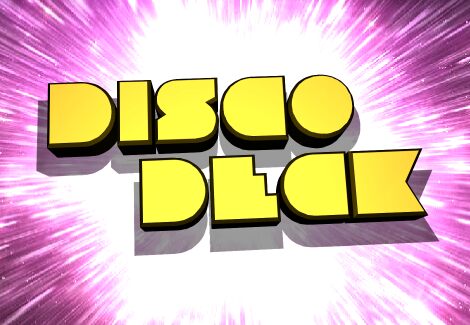
Disco Deck Italic od Iconian Fonts to groovy krój typu display, który przenosi Cię prosto na oświetlony neonami parkiet. Grube, pochylone litery sprawiają wrażenie, jakby ślizgały się po linii podstawowej, a wyraziste, zaokrąglone kształty przywodzą na myśl płyty winylowe i kule dyskotekowe. Zwarty rytm i pochylenie nadają każdemu słowu dynamiki, jakby tekst był uwięziony w błyskach stroboskopu.
Dzięki Disco Deck Italic nagłówki od razu krzyczą „impreza”, zanim jeszcze przeczytasz słowo. Ten darmowy font to naturalny wybór na klubowe ulotki, plakaty muzyczne, oprawę festiwali, grafikę w stylu retro, logotypy wydarzeń czy wyraziste gadżety. Świetnie sprawdza się w dużych rozmiarach – niech gra główną rolę, a w mniejszych tekstach połącz go z prostym, geometrycznym bezszeryfowym krojem, aby zachować czytelność, nie tracąc przy tym groove’u.